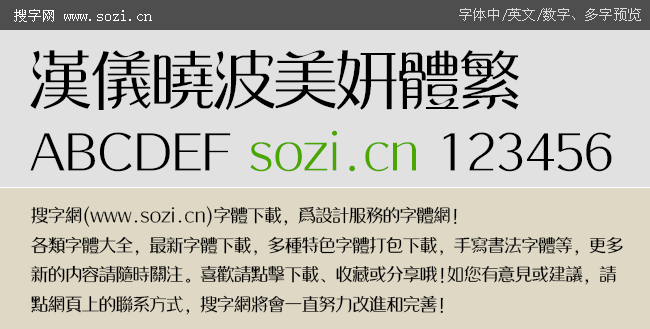
漢儀曉波美妍體繁
搜字網(wǎng)給大家提供一款漢儀曉波美妍體繁中文藝術(shù)字體下載。漢儀曉波美妍體是一款專為女性品牌量身定制的藝術(shù)字體,漢儀曉波美妍體極具美感和藝術(shù)風(fēng)格,效果與廣告渾然天成,審美和實(shí)用價(jià)值都非常高。適合化妝品廣告、女裝廣告設(shè)計(jì)、藝術(shù)雜志等場(chǎng)合使用。